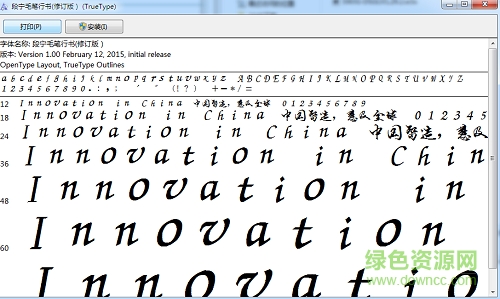
段寧毛筆行書修訂版是一款由段寧毛筆行書修改而來的電腦行書字體,字形飄逸大方,字體構(gòu)造端正,筆畫飛揚(yáng),充滿韻味,有喜歡的朋友歡迎下載使用!
段寧毛筆行書修訂版是在段寧毛筆行書的基礎(chǔ)上進(jìn)一步修改而成的,對常用字作了擴(kuò)充,部分字重新書寫重新做字模,字模的大小重新調(diào)整,排版時更美觀。